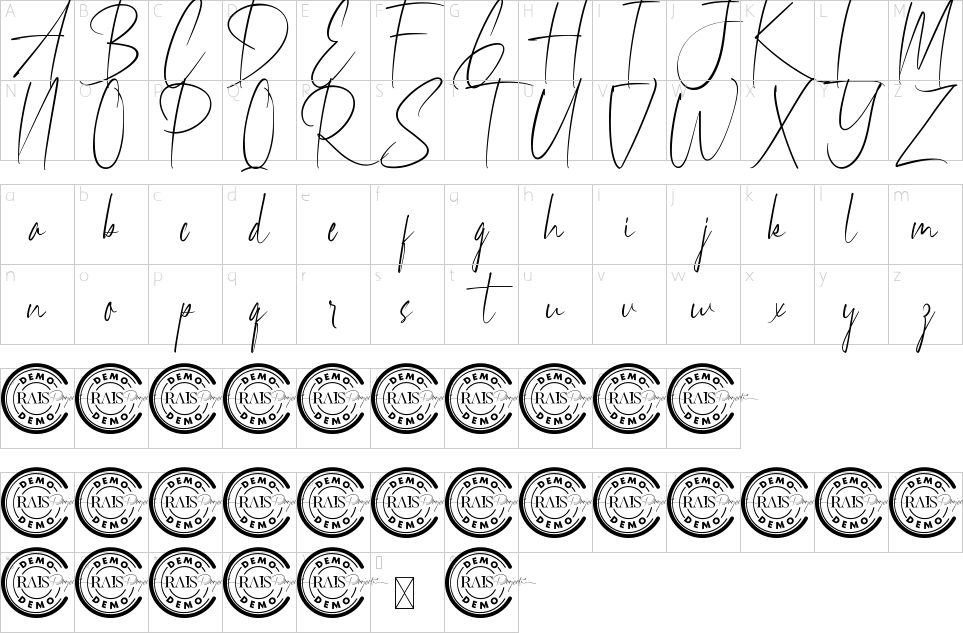
Descubra a beleza natural da Dothan Font em seu próximo projeto de design. Desenvolvida pela equipe do raisproject, esta elegante fonte vem para complementar sua obra com um toque sofisticado e versátil. Desfrute da simplicidade arquitetônica desta fonte, projetada exclusivamente para Windows e Mac, que já foi baixada 1.775 vezes pelo seu vasto público de designers. Adquira a Dothan Font hoje e seja parte da comunidade de criativos apaixonados por essa grata adição ao seu arsenal de ferramentas de design.